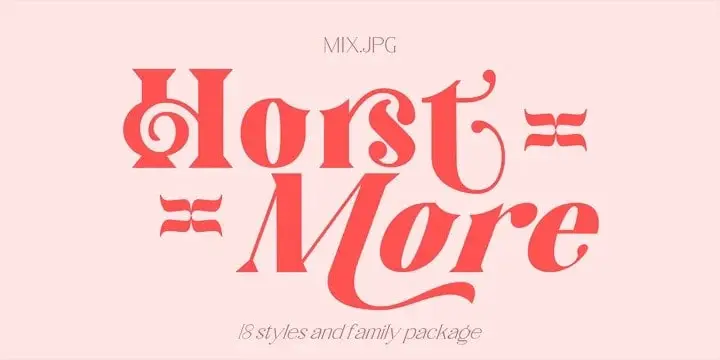
Horst More Serif é uma família de fóruns romanas que oferece uma variedade fascinante de alternativas e ligaturas para dar a sua marca aquele toque único. Introduzida pelo designer MIX.Jpg, esta fonte romana retro possui 18 tipos diferentes que cobrem um amplo espectro de aplicações tipoográficas, desde as marcas até o texto corporativo. Horst More é uma escolha inteligente para quem busca uma tipografia elegante e sofisticada. A sua versatilidade e personalização fazem deste uma opção perfeita para criar composições tipográficas distintas que agradam tanto aos olhos quanto ao ouvido do seu público. Com suas múltiplas alternativas e ligaturas, este conjunto de fóruns romanas oferece inúmeras maneiras de tornar seus projetos ainda mais profissionais e criativos. Seja você um designer gráfico, editor de conteúdo ou simplesmente alguém que aprecia belas tipografias, Horst More será a fonte ideal para iluminar seu trabalho com um toque sofisticado e personalizado.